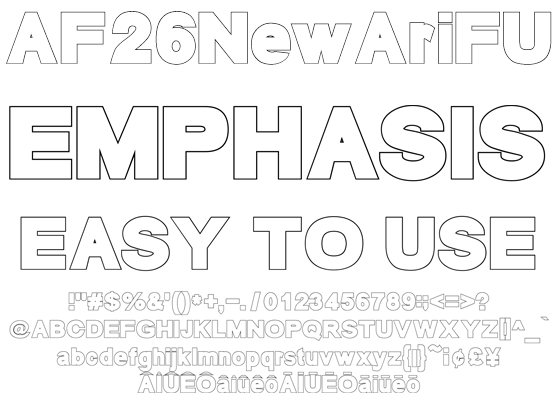
極太袋文字 AF26NewAriFU
AF26NewAriFU
極太で視認性を強調したサンセリフ袋文字欧文フォントです。バックカラーに同化させつつもインパクトを与えたい場所に適しています。平凡ながら極太デザインは違和感なくメッセージを浸透させます。記号類、マクロンやサーカムフレックスなどのダイアクリティカルマーク、訓令式やヘボン式で扱う Ô やŌを収録、人名地名でもお使い頂けます。